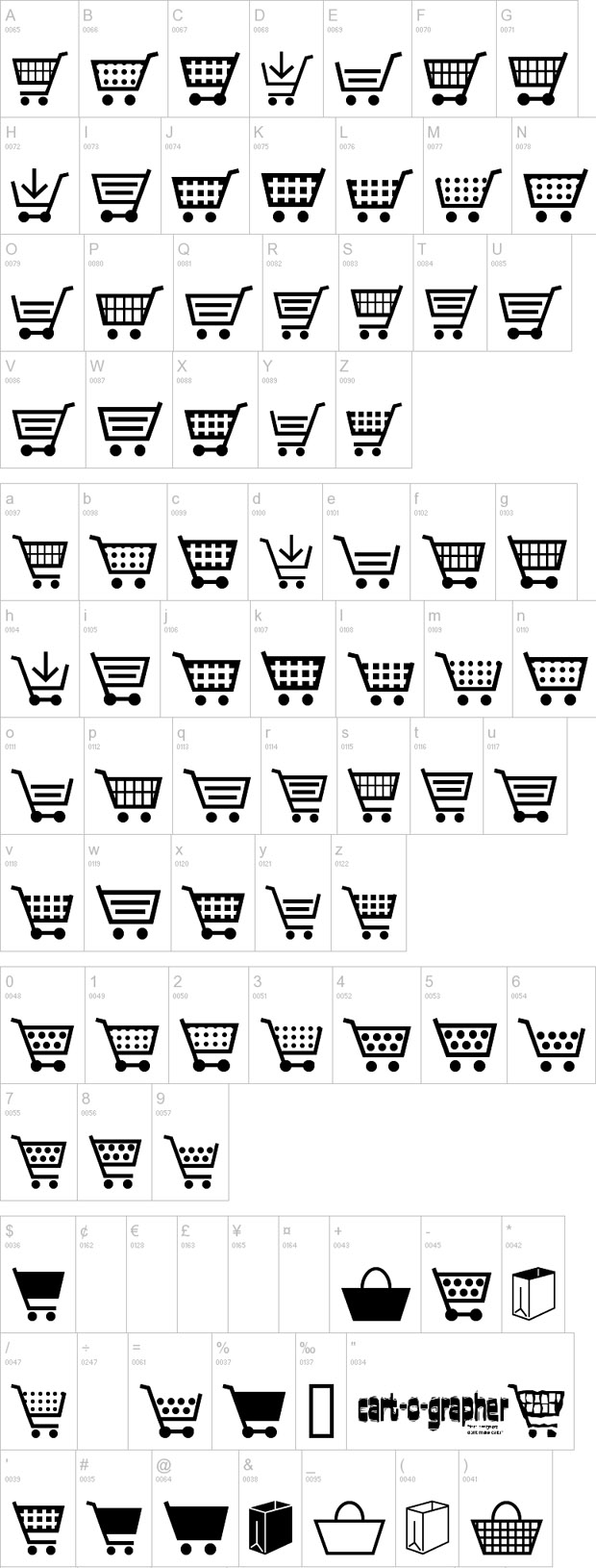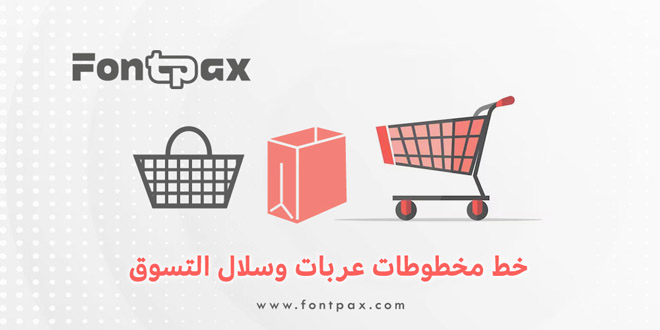
خط مخطوطات عربات وسلال التسوق .. خط أشكال عربات التسوق الشهيرة والسلال بطريقة الكليب آرت، يمكن استخدامها في برامج الأوفيس والتصميم المتنوعة، وهي متاحة للتحميل المجاني الآن.
خط مخطوطات عربات وسلال التسوق